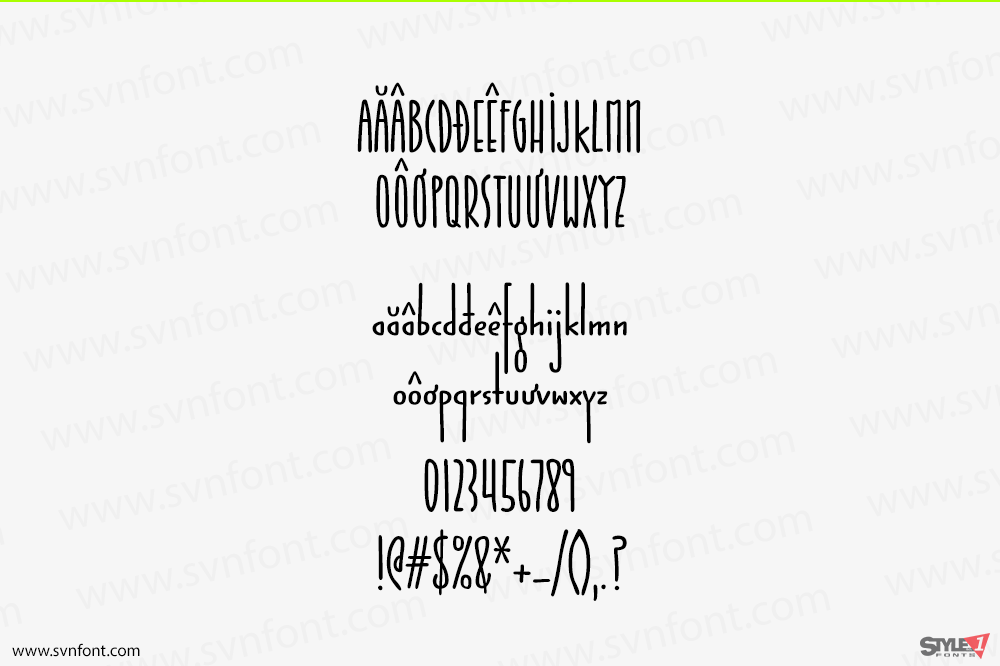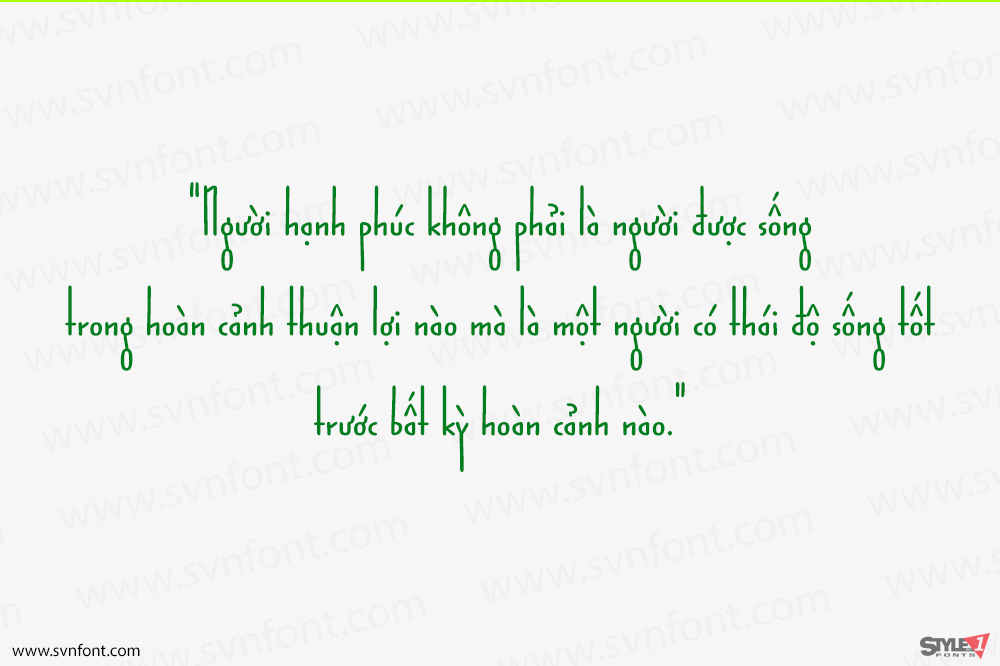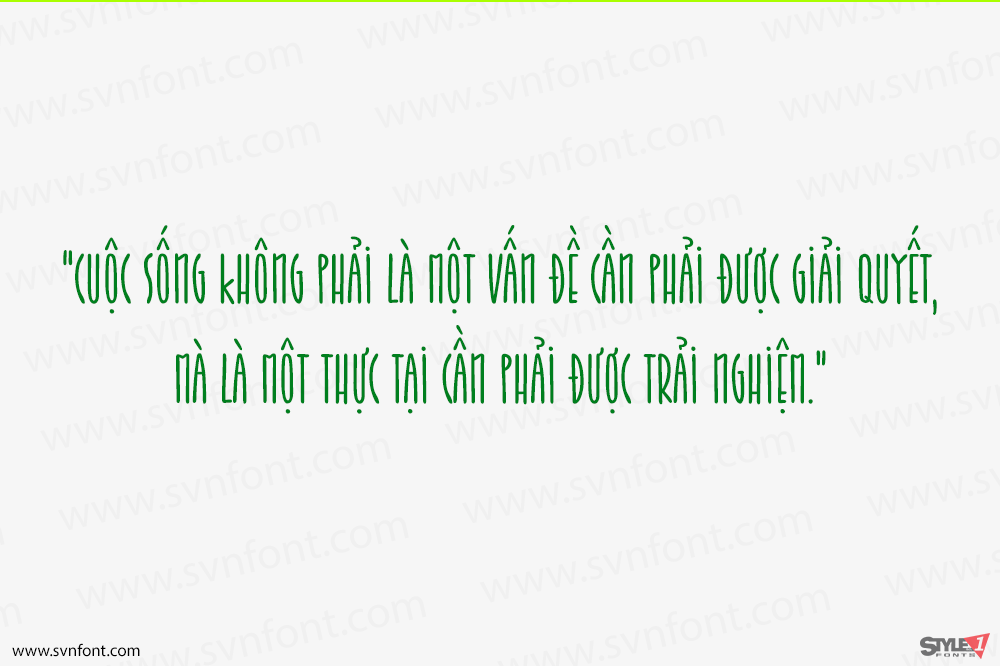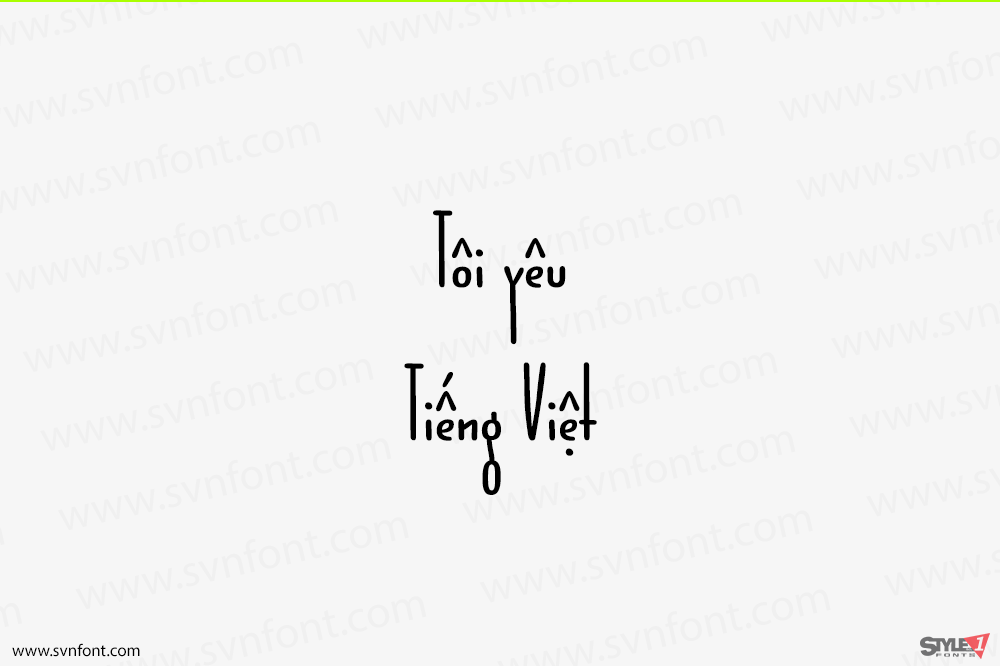
Jabana — lấy cảm hứng từ việc thưởng thức món “Schorle” (nước trái cây pha soda) trong các quán cà phê ở Hamburg, những đường cong viết tay mượt mà như nét bút dạ của Jabana. Font chữ thuộc thể loại viết tay, thích hợp cho các thiết kế về thủ công, trang trí, thiếu nhi…
Nhà thiết kế: Nils Thomsen
Nhà phát hành: TypeMates